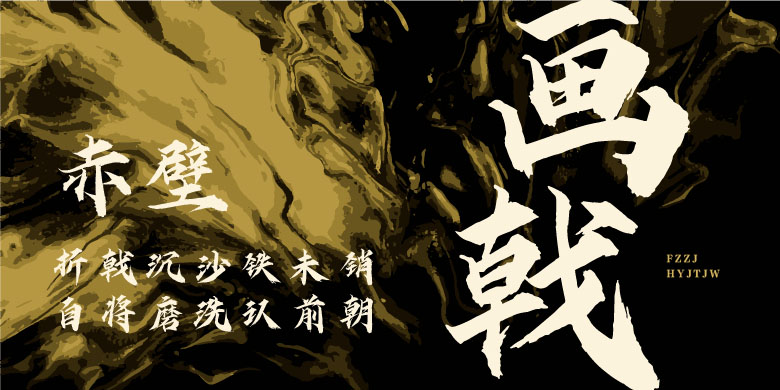
方正字迹-鸿远剑体简繁体
设计师: 刘剑鸿
方正字迹-鸿远剑体简繁体,方正字迹-鸿远剑体,作者是90后自由设计师刘剑鸿(鸿远),也是站酷推荐设计师,他从小热爱书法、画画,毕业于韶关学院艺术设计系,现致力于探索研究毛笔书法手写字体设计。此款字笔画粗细均匀,方正硬朗,字形笔触锋利如剑浑厚力强。是一款个性化商业手写字体,适合用于海报、游戏、影视综艺、广告、漫画、品牌标志设计等。